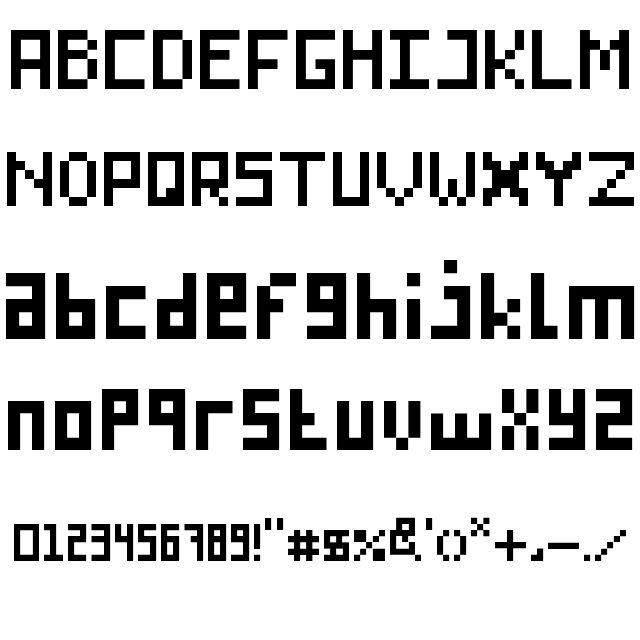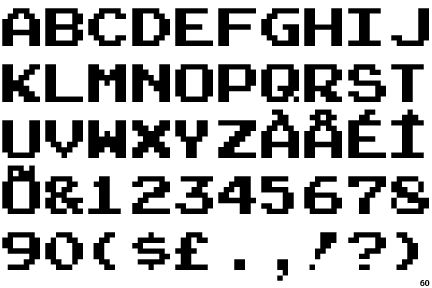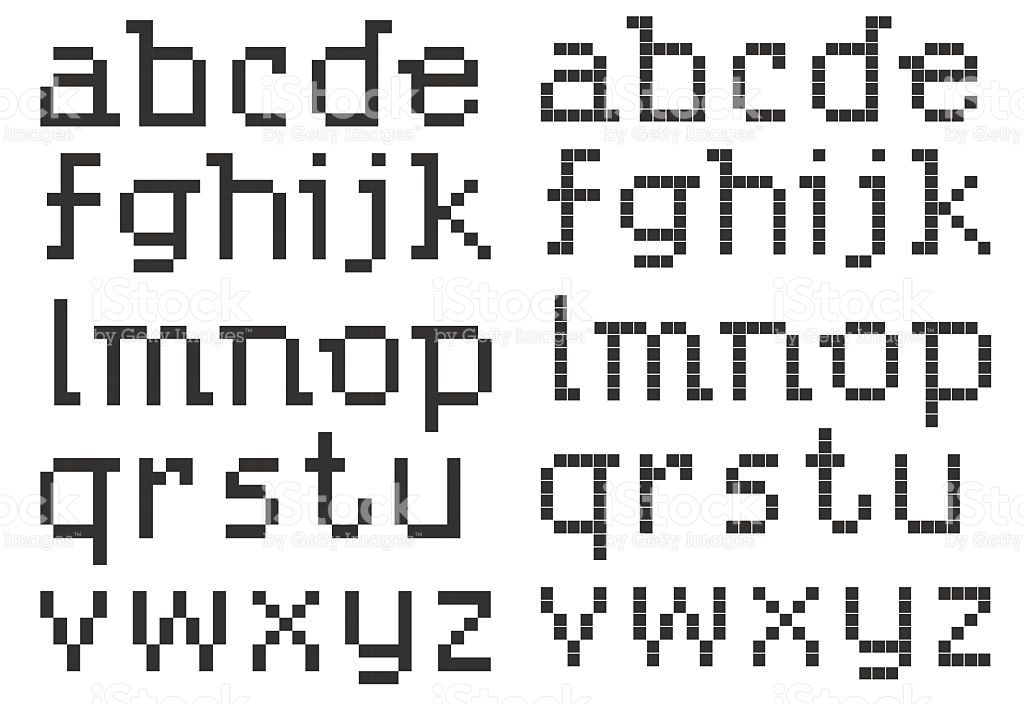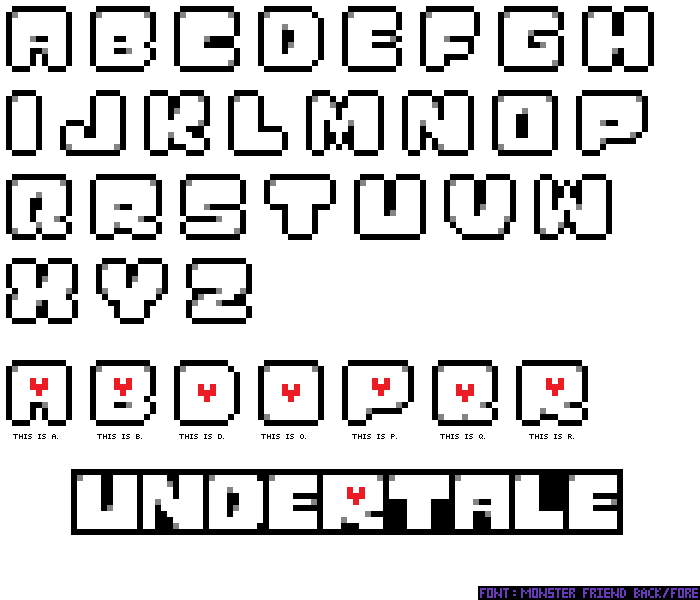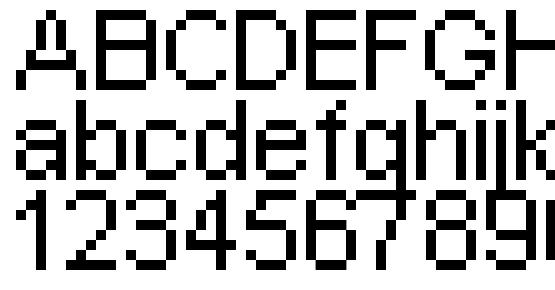
20+ лучших пиксельных шрифтов для ваших проектов
Эта коллекция классных пиксельных шрифтов перенесет вас в 1980-е годы, эпоху старых добрых аркадных игр.
Когда дело доходит до оформления заголовков в видеоиграх или разработки дизайна технологической тематики, ничто не сравнится с классическим пиксельным шрифтом. В нем есть что-то особенное: он вызывает у аудитории ностальгию и заставляет снова почувствовать себя ребенком.
Поэтому пиксельные шрифты идеально подходят для винтажных проектов. Их также можно довольно часто встретить в дизайне футболок, на обложках видео в YouTube, в социальных сетях и т.д.
Мы собрали для вас отличную коллекцию пиксельных шрифтов. Здесь представлено множество разных стилей — вы точно найдете что-то подходящее для своего следующего проекта. Только взгляните!
Если вы ищете многофункциональный пиксельный шрифт, аккуратный и не слишком декоративный, лучшего варианта вам не найти. Пиксельные буквы выглядят оригинально, но без сильных искажений, что обеспечивает высокую читабельность. Шрифт включает как прописные, так и строчные буквы.
Broken Console — геометрический пиксельный шрифт. Он представлен в трех различных стилях: обычный, двухпиксельный и с тенью. Шрифт состоит из прописных букв, поэтому он больше всего подходит для создания массивных заметных заголовков.
Этот классический пиксельный шрифт был вдохновлен ретро-аркадами. Он состоит из прописных букв и включает несколько дингбатов (типографские знаки для оформления текста) с персонажами из классических игр, таких как Space Invaders (Космические захватчики).